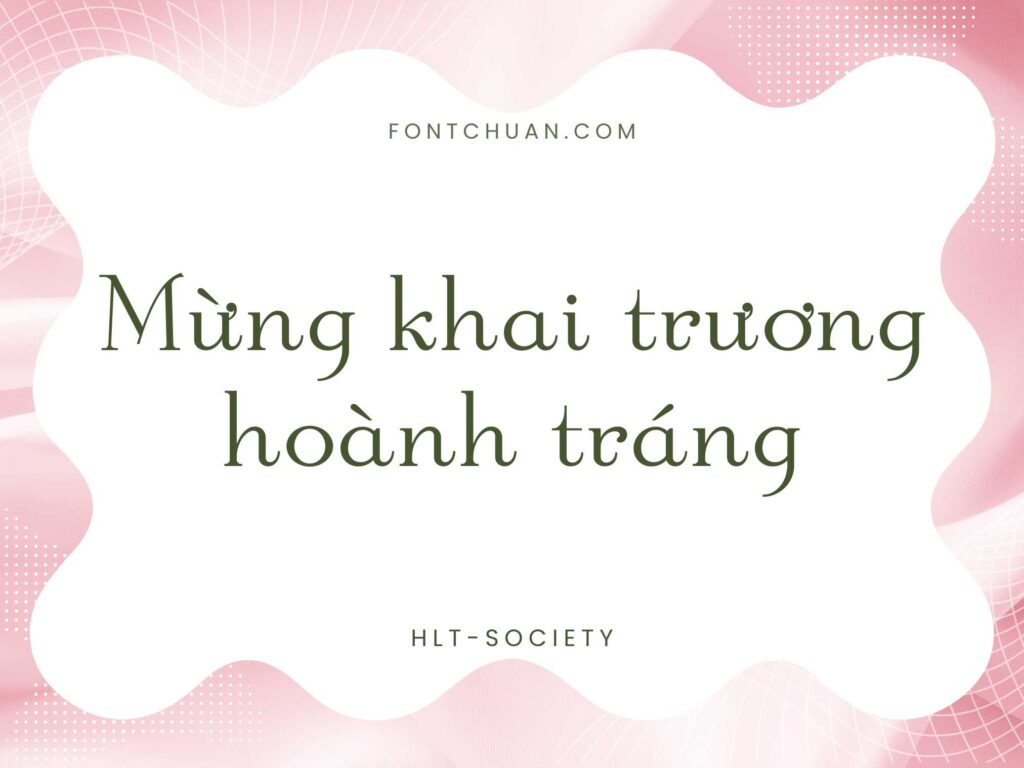
Font HLT Society Việt Hóa
Society là một phông chữ serif thanh lịch, mang phong cách cổ điển nhưng vẫn hiện đại và sang trọng. Font này được thiết kế với các đường nét thanh mảnh, tạo nên sự tinh tế và chuyên nghiệp cho các dự án thiết kế. Với sự Việt hóa của HLT, Society hỗ trợ đầy đủ các ký tự tiếng Việt, giúp người dùng dễ dàng áp dụng trong các thiết kế đa ngôn ngữ. Thành viên của Font Chuẩn đã sưu tầm và chia sẻ phông chữ này nhằm đáp ứng nhu cầu đa dạng của cộng đồng thiết kế.
Về đặc điểm thiết kế, Society sở hữu kiểu dáng serif tinh tế, với độ tương phản nhẹ giữa các nét thanh và nét đậm, mang lại sự mềm mại và sang trọng. Phông chữ này đặc biệt phù hợp cho các ứng dụng như thiết kế thương hiệu, tiêu đề, biên tập sách, bìa tạp chí và các ấn phẩm quảng cáo, nơi cần sự rõ ràng và đẳng cấp. Ngoài ra, Society cũng thích hợp cho các sự kiện như lễ hội, sinh nhật, Valentine và Trung thu, tạo không khí trang trọng và lãng mạn. Trong lĩnh vực ngành nghề, Society được ứng dụng rộng rãi trong quảng cáo, thiết kế thiệp cưới, giáo dục và công nghệ, góp phần tạo nên sự tinh tế và chuyên nghiệp cho các sản phẩm và thương hiệu.